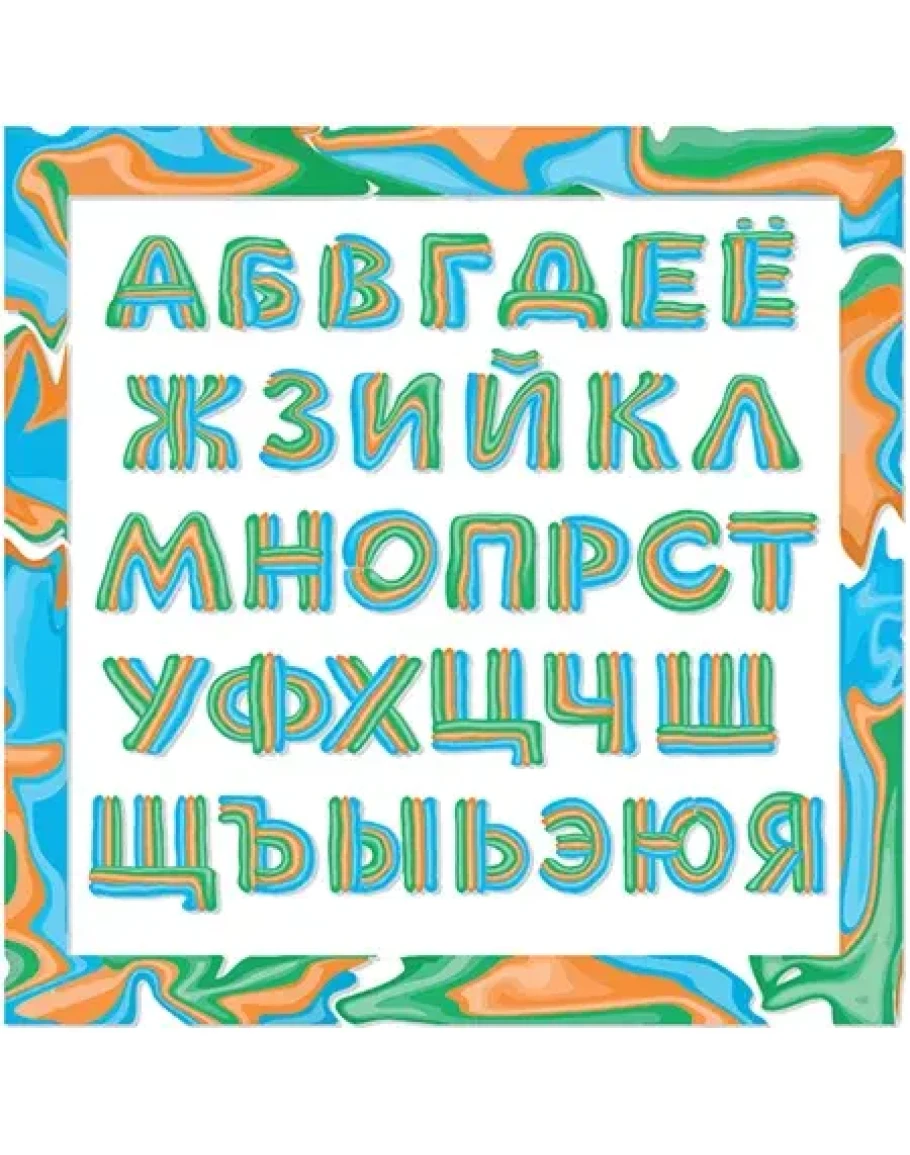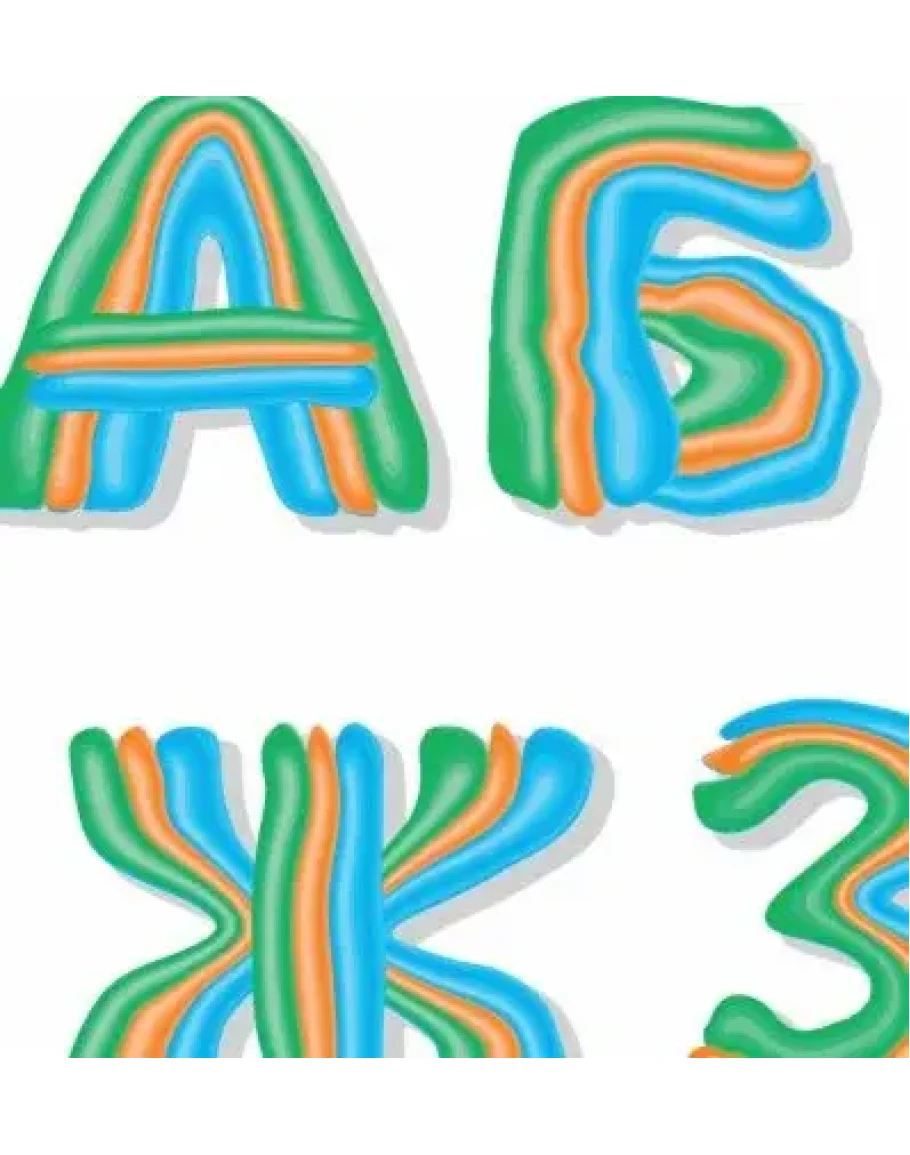
Векторный декоративный шрифт, все заглавные буквы русского алфавита в виде вылепленных знаков из цветного пластилина или нарисованных масляной разноцветной краской. Для использования в дизайне, оформления заголовков и названий. Файлы в векторе для CorelDraw и Иллюстратора, а также растр высокого разрешения в jpg и на прозрачном фоне в формате png. Прямая ссылка для скачивания архива.